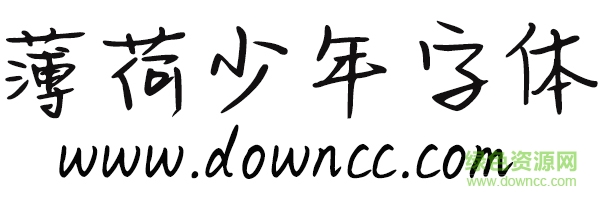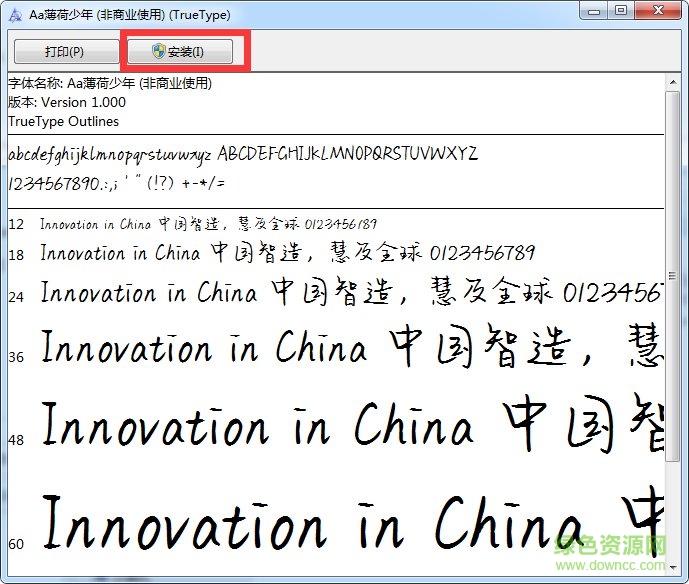
aa薄荷少年字體ttf格式是一個(gè)免費(fèi)電腦字體資源。小編為大家提供的這款字體外觀看起來很飄逸,有點(diǎn)行書的風(fēng)格。常用語設(shè)計(jì)行業(yè)!需要的用戶快來綠色資源網(wǎng)下載使用吧。
薄荷少年體字體是一款以黑體為原形打造的藝術(shù)字體,加了一點(diǎn)點(diǎn)的潦草風(fēng)格,整體效果看上去非常簡(jiǎn)潔大方,很受廣大網(wǎng)友們的喜愛!